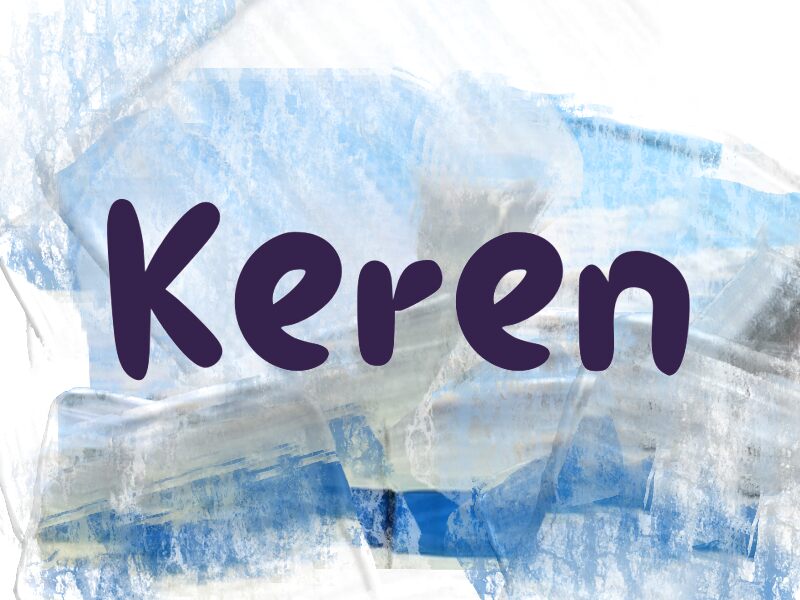
Keren od Wep to darmowy krój typu comic display o masywnym, ręcznie rysowanym charakterze. Litery wyglądają miękko, są nieco „napuchnięte” i celowo nierówne, a zaokrąglone łączenia oraz duże, przyjazne łuki nadają całemu fontowi swobodny, odręczny rytm.
Idealnie sprawdzi się na opakowaniach produktów dla dzieci, w menu kawiarni, przy projektach naklejek, plakatach szkolnych oraz w grafikach do mediów społecznościowych – wszędzie tam, gdzie darmowy font ma emanować ciepłem, a nie sterylną perfekcją. Keren świetnie nadaje się również do krótkich nagłówków i logotypów, ponieważ dzięki grubym, poduszkowatym literom nawet proste słowa nabierają życia i luźnego charakteru.
Keren
Prezentacja i próbka wizualna czcionki Keren